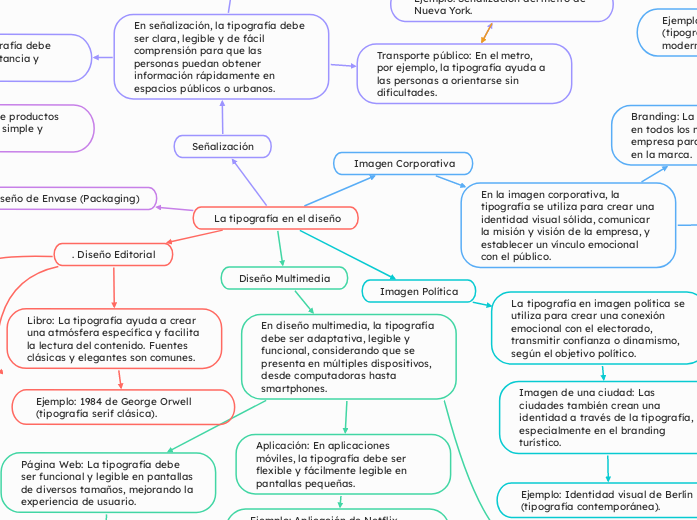
La tipografía en el diseño
Diseño Multimedia
En diseño multimedia, la tipografía debe ser adaptativa, legible y funcional, considerando que se presenta en múltiples dispositivos, desde computadoras hasta smartphones.
Aplicación adicional: Aplicación de biblioteca digital (tipografía que facilita la lectura en dispositivos móviles).
Aplicación: En aplicaciones móviles, la tipografía debe ser flexible y fácilmente legible en pantallas pequeñas.
Ejemplo: Aplicación de Netflix (tipografía estilizada pero legible en móviles).
Página Web: La tipografía debe ser funcional y legible en pantallas de diversos tamaños, mejorando la experiencia de usuario.
Ejemplo: Página web de Amazon (tipografía clara y fácil de leer).
Imagen Política
La tipografía en imagen política se utiliza para crear una conexión emocional con el electorado, transmitir confianza o dinamismo, según el objetivo político.
Imagen de una ciudad: Las ciudades también crean una identidad a través de la tipografía, especialmente en el branding turístico.
Ejemplo: Identidad visual de Berlín (tipografía contemporánea).
Imagen Gubernamental: Los gobiernos usan la tipografía en documentos oficiales, campañas y comunicaciones para transmitir autoridad y confianza.
Ejemplo: Material del gobierno de AMLO en México (tipografía simple y moderna).
Campañas Políticas: El uso de tipografía en las campañas ayuda a generar una imagen de liderazgo o cercanía, dependiendo del mensaje político.
Ejemplo: Cartel de la campaña de Barack Obama (tipografía sans-serif, clara y moderna).
Imagen Corporativa
En la imagen corporativa, la tipografía se utiliza para crear una identidad visual sólida, comunicar la misión y visión de la empresa, y establecer un vínculo emocional con el público.
Branding: La tipografía se aplica en todos los medios impresos de la empresa para crear consistencia en la marca.
Ejemplo: Logotipo de Apple (tipografía minimalista y moderna).
Logotipo: El logotipo usa tipografía para construir una identidad visual única y fácilmente reconocible.
Ejemplo adicional: Branding de Google (tipografía accesible y amigable).
Ejemplo: Material impreso de Nike (tipografía deportiva y dinámica).
Señalización
En señalización, la tipografía debe ser clara, legible y de fácil comprensión para que las personas puedan obtener información rápidamente en espacios públicos o urbanos.
Museos: En las exposiciones, la tipografía ayuda a presentar la información de manera clara y ordenada.
Ejemplo: Carteles informativos en museos.
Transporte público: En el metro, por ejemplo, la tipografía ayuda a las personas a orientarse sin dificultades.
Ejemplo: Señalización del metro de Nueva York.
Aeropuertos: La tipografía debe ser legible a larga distancia y rápida de procesar.
Ejemplo: Señalización en el aeropuerto de Heathrow.
Diseño de Envase (Packaging)
En el diseño de envase, la tipografía se utiliza para atraer al consumidor, comunicar la identidad de la marca y proporcionar información importante sobre el producto.
Ejemplo: Packaging de productos orgánicos (tipografía simple y natural).
Ejemplo: Packaging de Chanel (tipografía elegante y minimalista).
Ejemplo: Botella de Coca-Cola (tipografía cursiva que transmite tradición y frescura).
. Diseño Editorial
Cartel: En los carteles, la tipografía es clave para transmitir el mensaje de forma rápida y efectiva, ya que se busca captar la atención a primera vista.
Ejemplo: Cartel de la película The Godfather (tipografía solemne y fuerte).
Revista: Se usa para comunicar la identidad de la revista, reflejar su tono y captar la atención del lector. La tipografía puede ser más experimental o moderna.
Ejemplo: Vogue (tipografía estilizada y moderna).
Libro: La tipografía ayuda a crear una atmósfera específica y facilita la lectura del contenido. Fuentes clásicas y elegantes son comunes.
Ejemplo: 1984 de George Orwell (tipografía serif clásica).